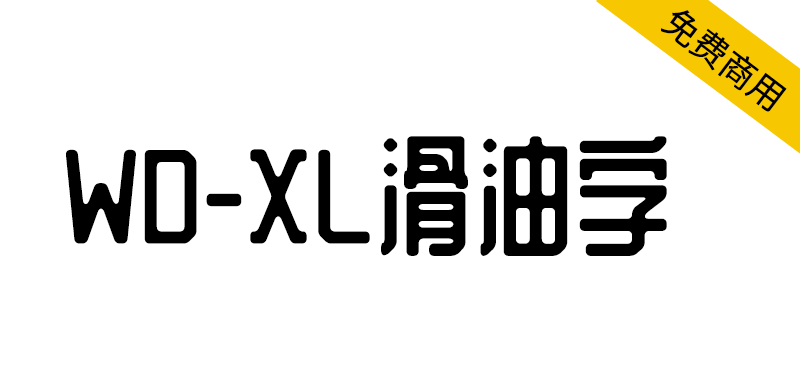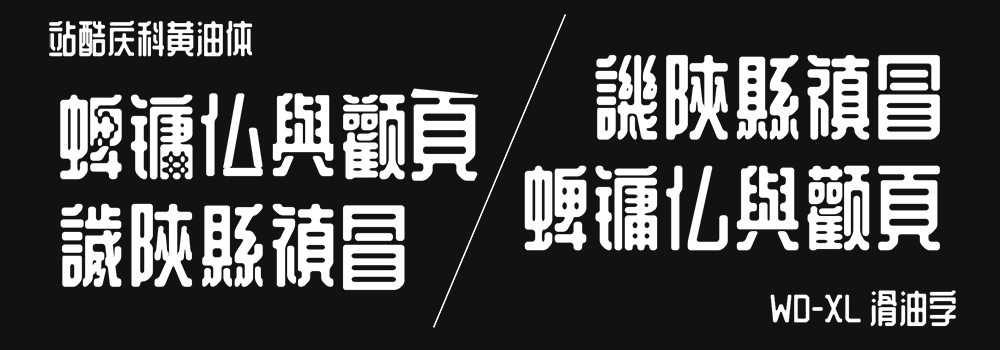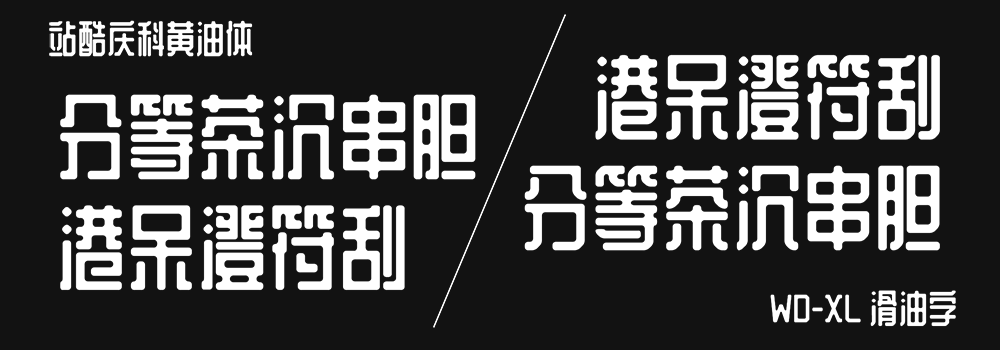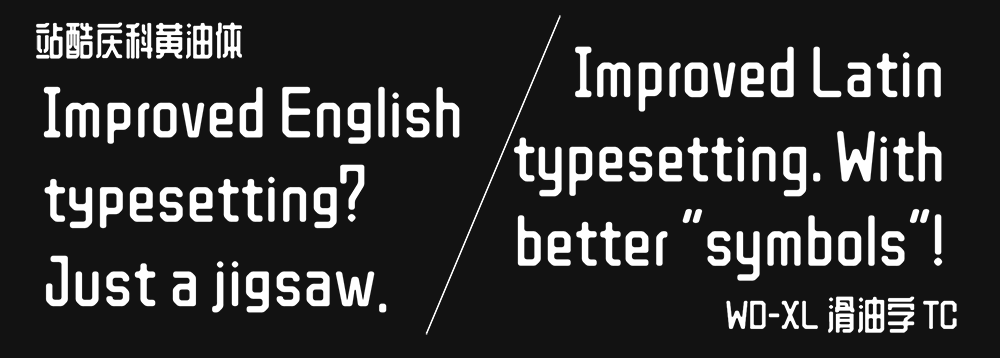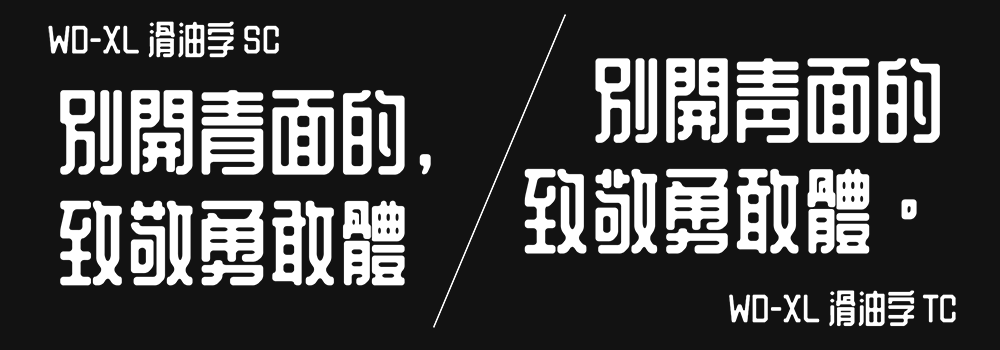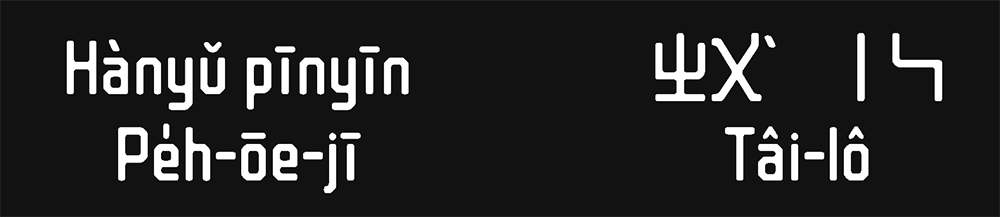
WD-XL 滑油字是在站酷庆科黄油体的基础上为繁体(正体)中文进行常用字补字扩充,让其能够适配繁体(正体)中文环境,并且也补全标准中文字体所需的标点符号和功能。目前本字体支援简体中文、繁体(正体)中文、台语、客语、粤语的常用字,也支援白话字和台罗拼音,日常排版使用绝无问题。
WD-XL 滑油字 是基于 站酷庆科黄油体 的字体进行繁体字补字,并且修整了标点符号及增加了中文排版所需要的符号(如汉语拼音及注音符号)。此外,本字体也改进了原字体的许多问题:
但是如果详细查看,部分汉字其实并没有 45° 右下斜角。本字体 1.100 版已经统一了此特征,让全部汉字视觉效果一致:
WD-XL 滑油字 的西文部分也经过检查修整,确保其更适合西文排版。
原字体已经数年未更新。WD-XL 滑油字 除了修改问题以外,也聆听了繁体中文排版界的需求,为繁体中文排版进行了修改增删,制作了 WD-XL 黄油体 TC 版本。TC 版依据更适合印刷的传承字形进行参考及修改以匹配原字体风格。
WD-XL 滑油字 还制作了汉语拼音、注音符号、白话字、台罗拼音的符号呢!你可以用这个字体来制作专业排版了!
未来 WD-XL 滑油字 将会尝试更多 OpenType 功能(主要于西文排版),敬请期待!